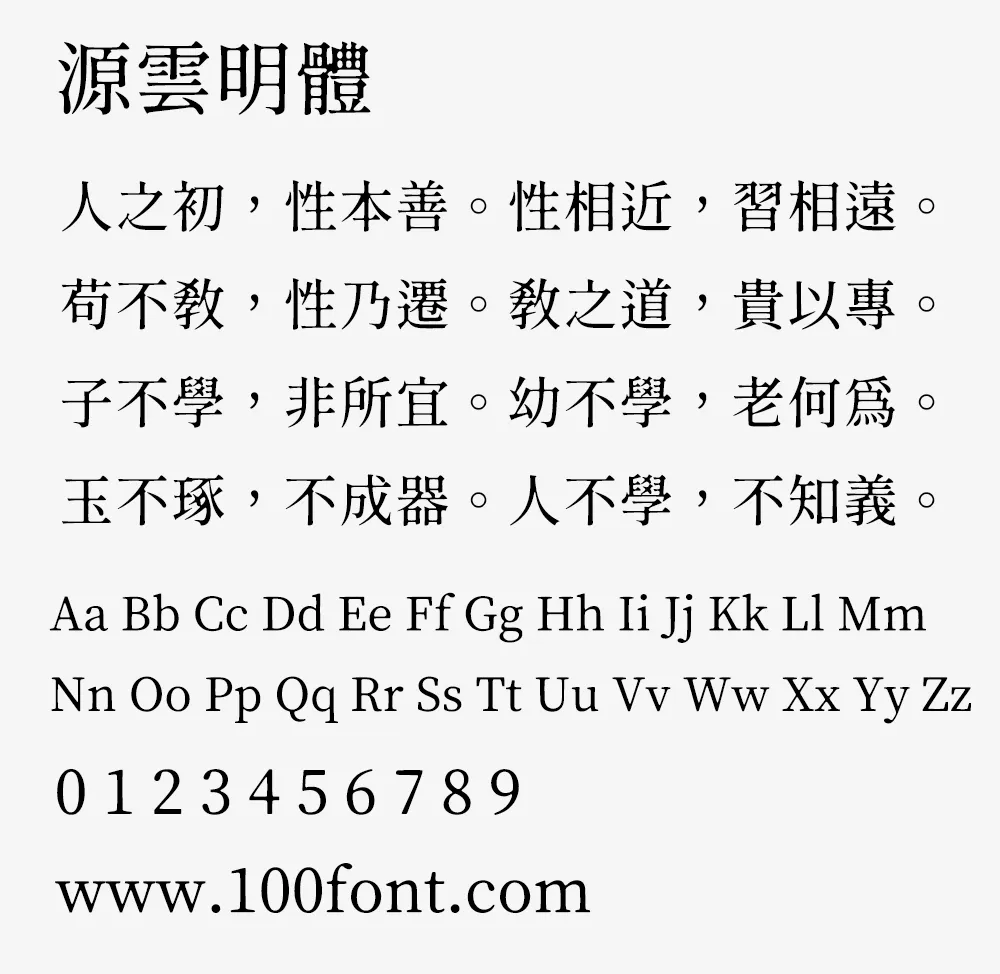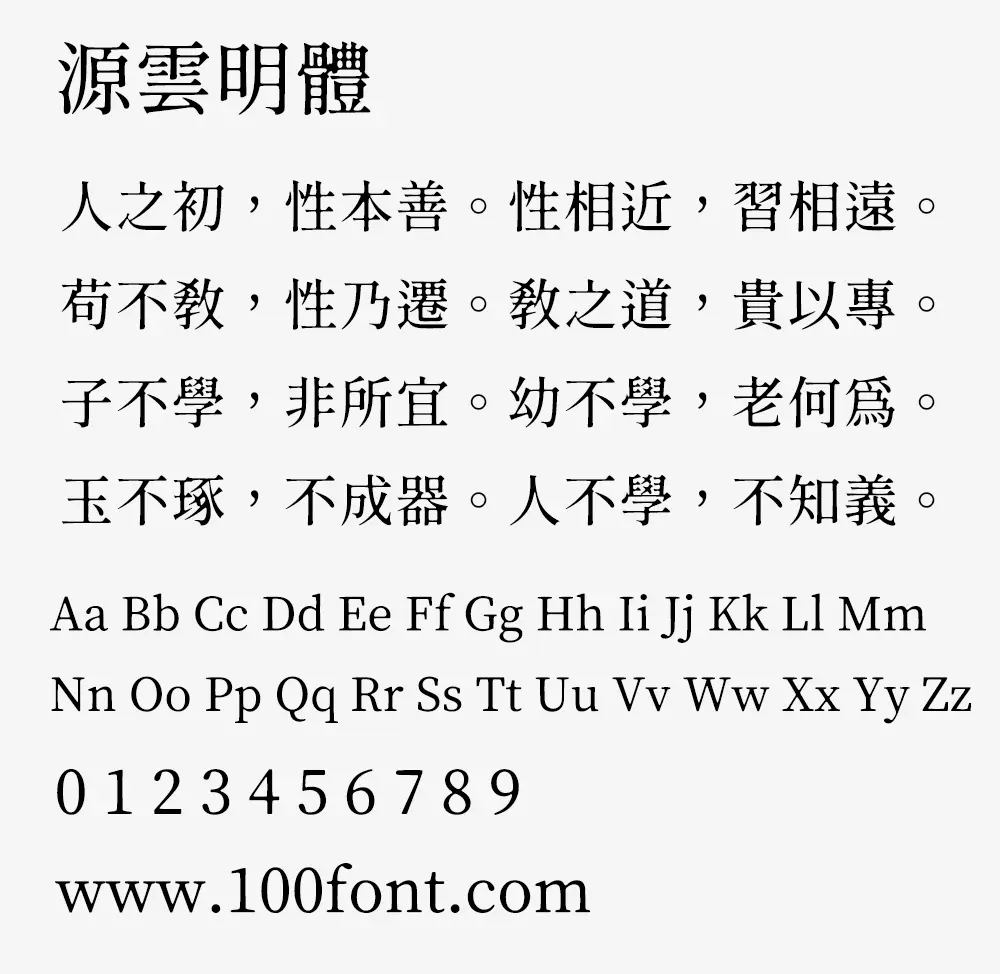
源雲明體由臺灣字型社團「字嗨」管理員 But Ko基於“思源宋體”修改衍生而來,筆畫交叉處有朦朧處理,懷舊而帶點感性的繁體中文字型,字體改造雖以計算機程序自動進行,但在一些細節調整後可以明顯感受出不同效果,源雲明體在橫筆的起筆及豎筆的起筆、收筆處加入粗細變化,筆畫交叉處有朦朧處理。
注意提醒:這款字體主要適用於繁體中文,雖然也支持簡體中文,但是簡體可能會出現錯別字等情況。